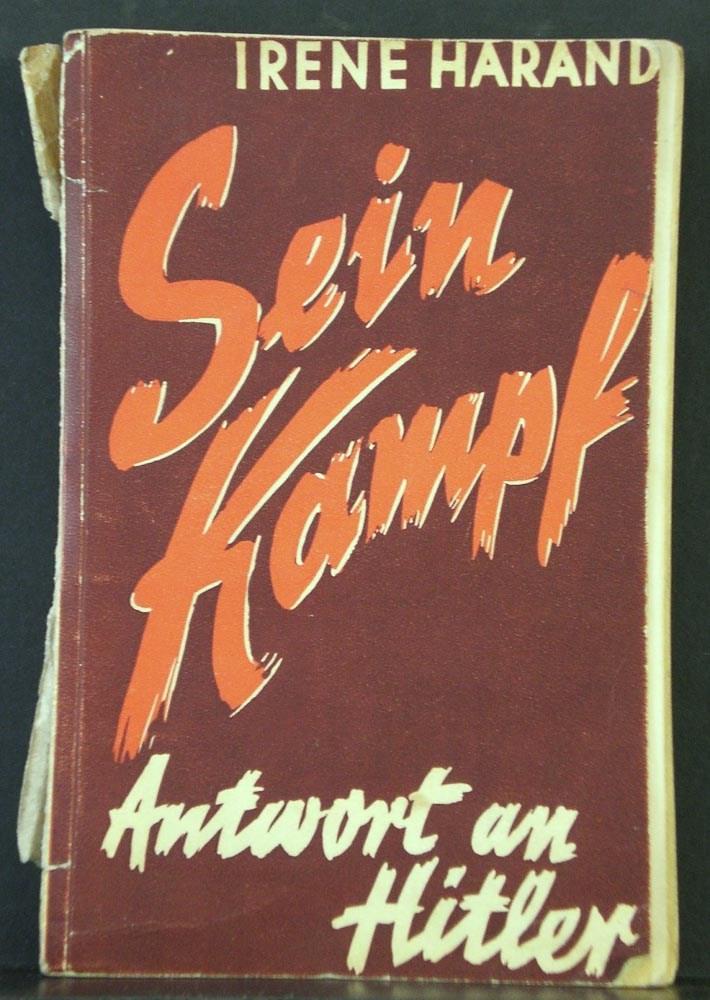
Geschichte - Typographie im III. Reich
Ich suche für eine zeithistorische Arbeit (30er) eine typische Typographie
(kalligraphischen Eindruck). Anhand habe ich ein Muster.
Wer kann mir dabei helfen - eventuell auch den Namen, sofern dieser Typ
genormt ist, mitzuteilen.